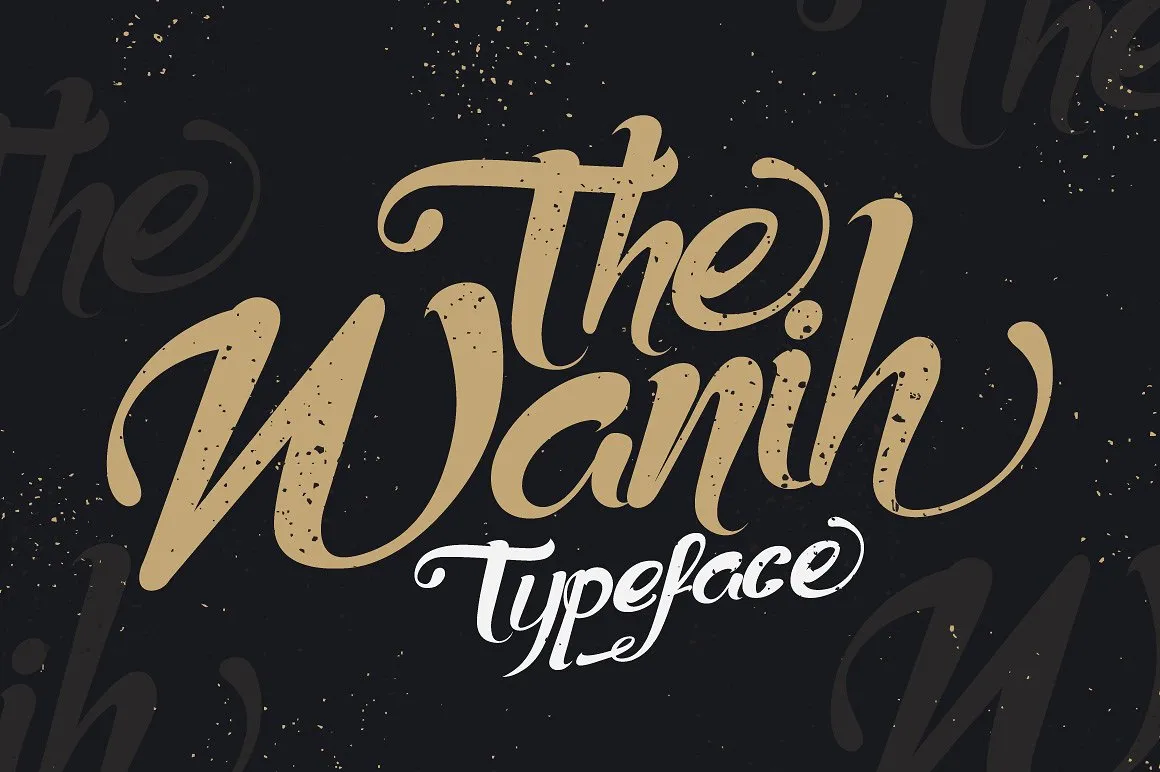
Introduzimos Wanih! Uma nova família de fontes círculo script com um toque elegante, casual e bonito. É perfeito para criar designs como tatuagens, headlines, logotipos e até mesmo para estampas de roupas ou adereços. Wanih transmite um estilo urbano único, misturado com uma técnica handmade única. Perfeita tanto para aqueles que procuram uma fonte sofisticada quanto para quem busca algo mais casual e descontraído. Wanih é perfeitamente adaptável a diferentes aplicações, tornando-a uma excelente escolha para designers de logotipos ou aquelas pessoas que querem dar um toque especial aos seus designs digitais. Seja você criando sua própria marca personalizada ou adicionando um design único ao seu próximo trabalho de arte digital, Wanih está aqui para te ajudar a expressar sua identidade visual. A sua elegância e casualidade fazem deste fonte uma escolha versátil e impecável tanto para projetos profissionais quanto pessoais. Não perca tempo: experimente Wanih hoje!